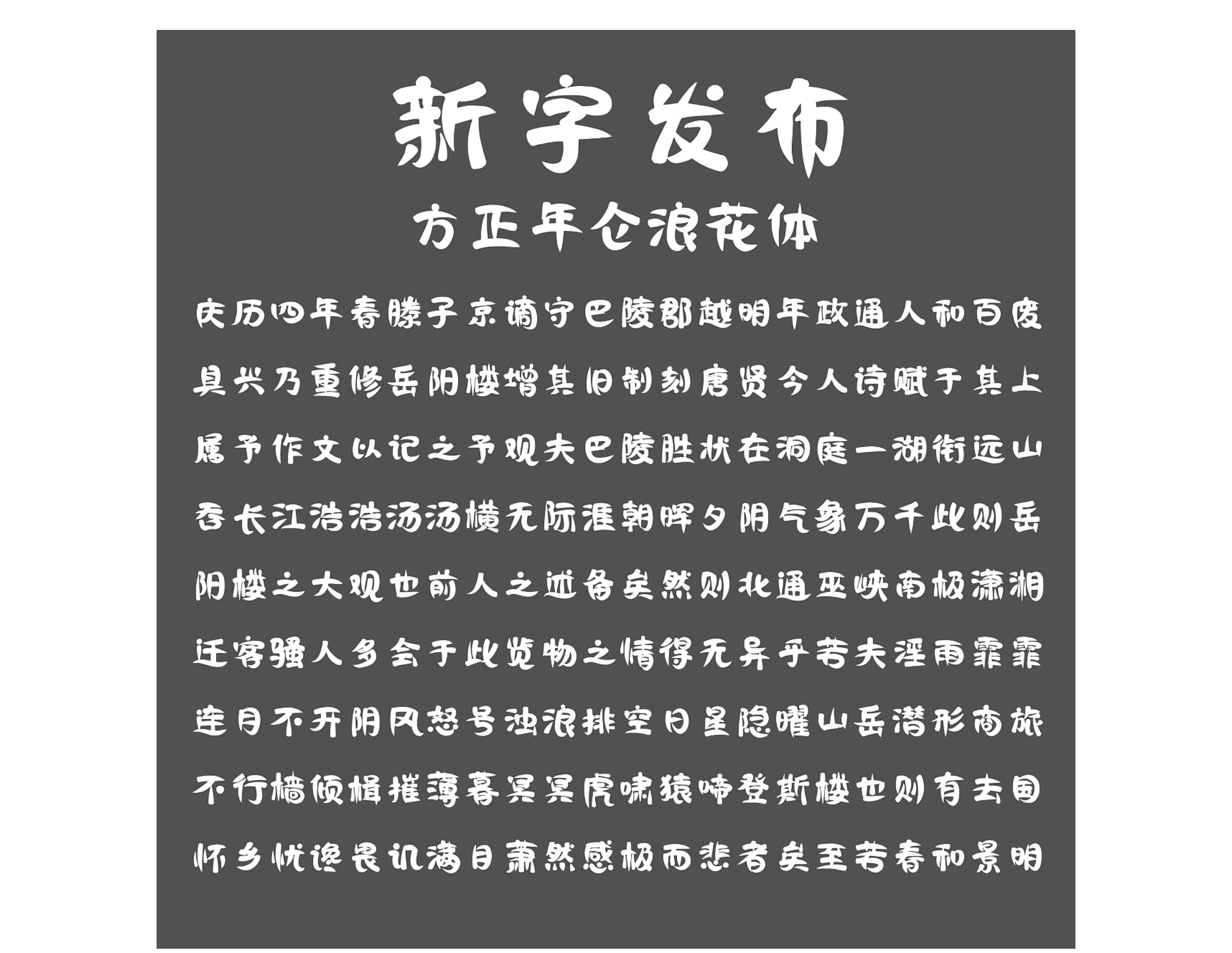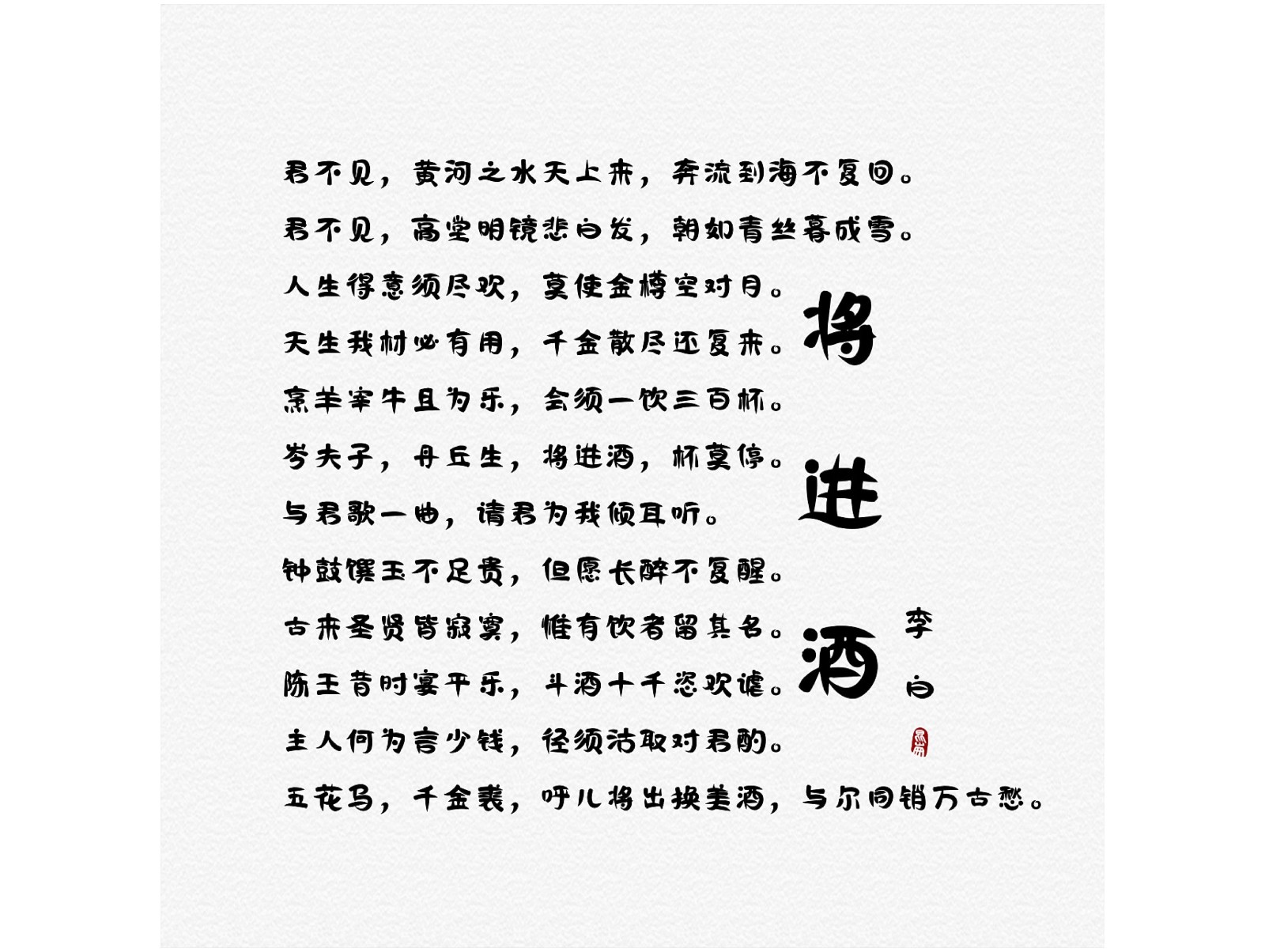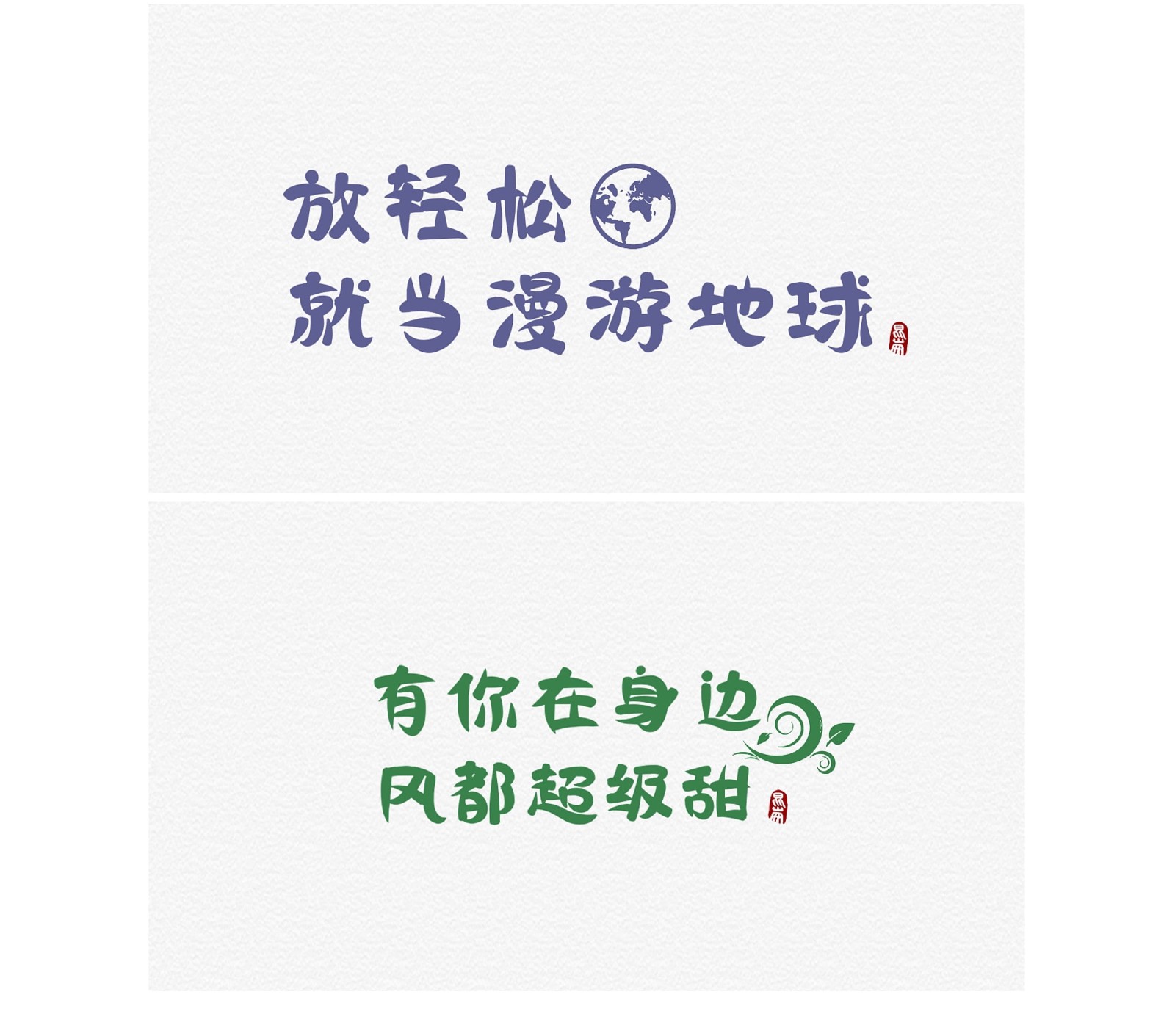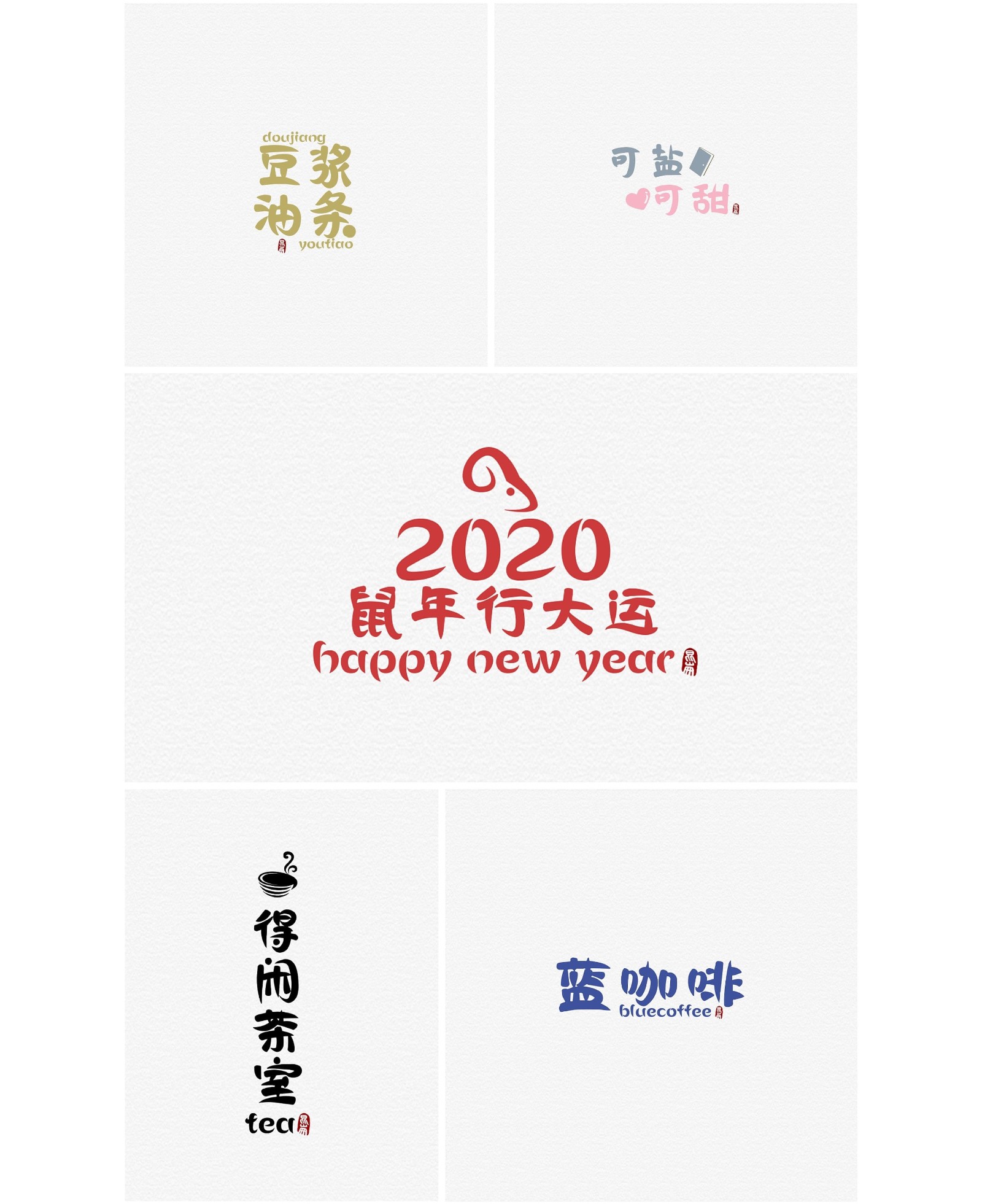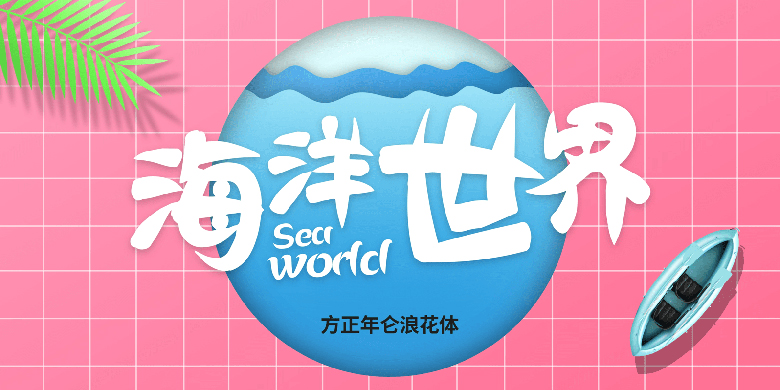
方正年仑浪花体
字体品牌: 方正字库设计师:刘一仑 字体分类:创意书写 字体属性:精品字 字符集:大陆简体(GB2312-80)、简繁扩展(GBK) 发布时间: 2020
作者刘一仑,设计灵感来源于作者在一场美术展中看到的一幅画,浑圆的浪花与流线型的水波形成了惬意的场景,就尝试把这种感觉用在字体上,把笔画做成流线型的,点设计成圆形,在此基础上加以修改,做出了这款字库。